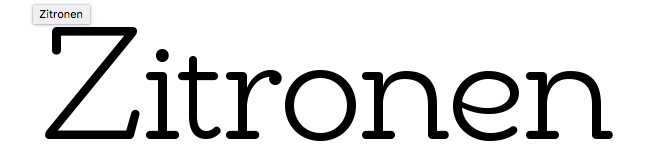
Welche Sans Serif passt zu Chennai Slab?
Ich suche eine passende Fließtext Schrift zur Chennai Slab. Die Fließtext Schrift sollte am besten sans serif sein, damit das Schriftbild nicht zu "niedlich" wird, da die Chennai sehr schnörkelig ist. Sollte aber jemand die perfekte Serif Schrift zur Chennai Slab kennen....würde ich den Tipp auch von Herzen gerne annehmen.
Es werden keine seitenlangen Texte geschrieben, aber die Schrift sollte gut lesbar und angenehm fürs Auge sein.
Zusammengefasst:
_Fließtextschrift zur Chennai Slab
_gut lesbar
_nicht zu technisch
_nicht zu niedlich